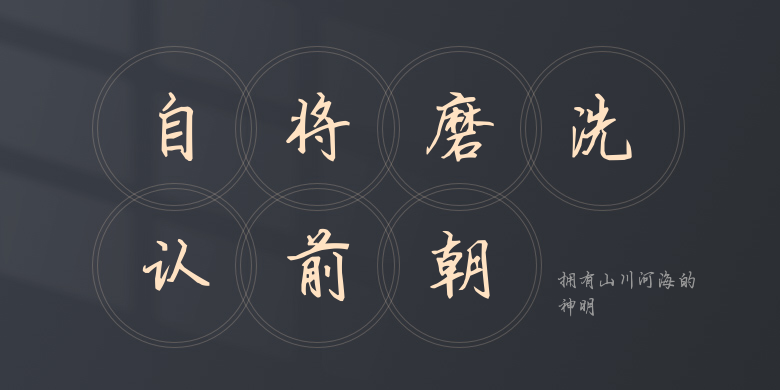
拥有山川河海的神明
拥有山川河海的神明,这款字体结构工整、笔画清晰,兼顾美观与易读性,适用于标题、正文、海报、包装、LOGO 等多种场景。字形优雅稳定,风格百搭耐看,适配日常排版与创意设计,让文字呈现更舒适、更具质感。拥有山川河海的神明一笔一画,皆是细节,以均衡的比例、流畅的线条打造舒适视觉体验,字形端正大气,风格简约现代。无论是商业设计、品牌宣传还是日常排版,都能轻松驾驭,让文字更有格调与力量。拥有山川河海的神明字体下载。